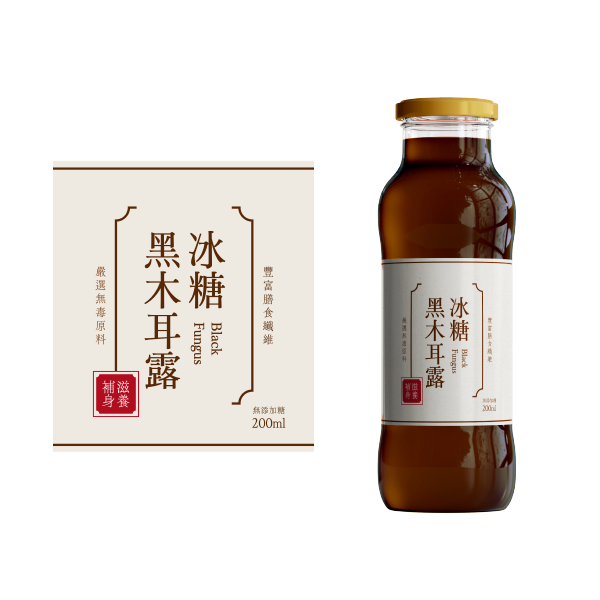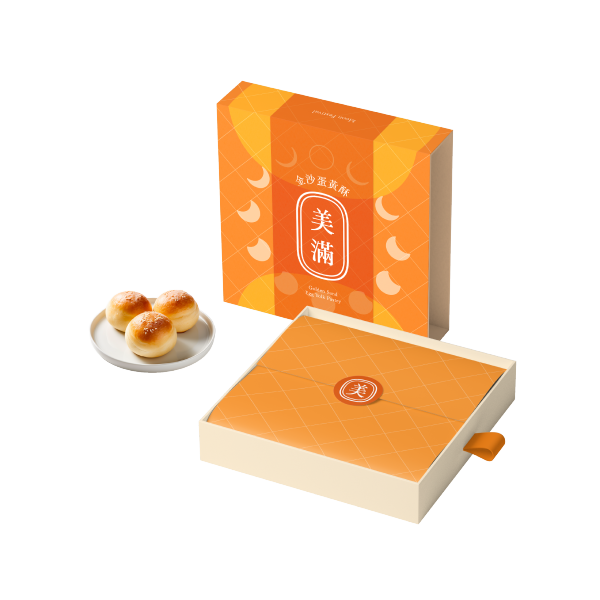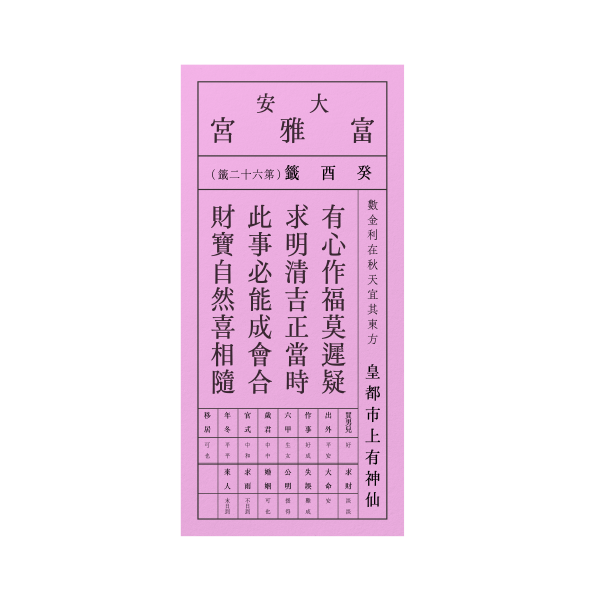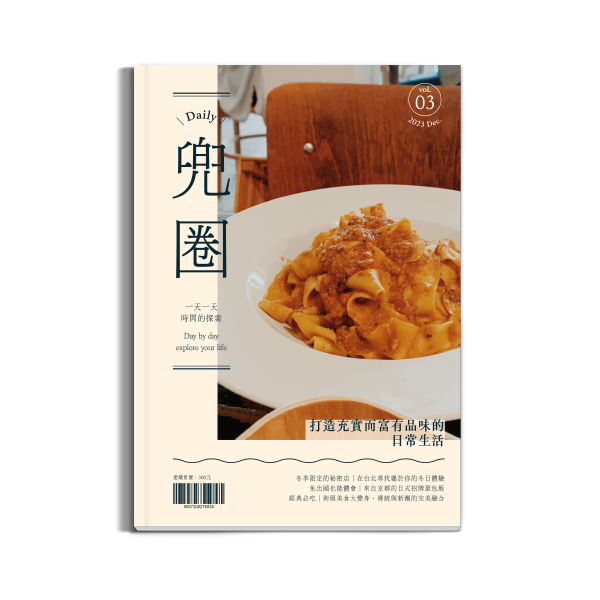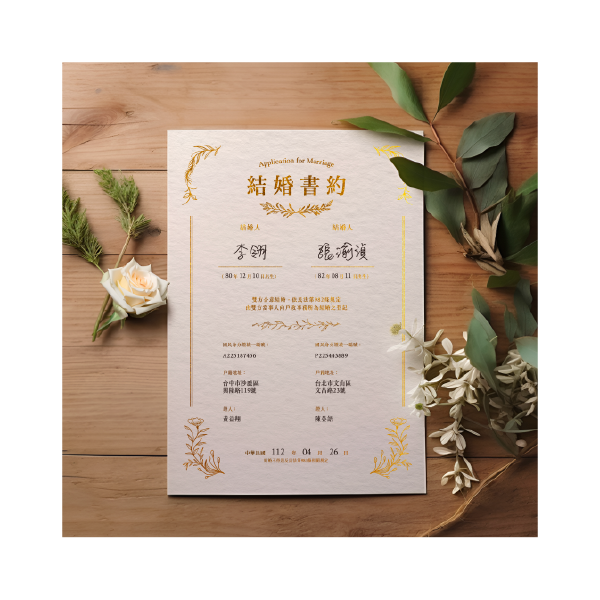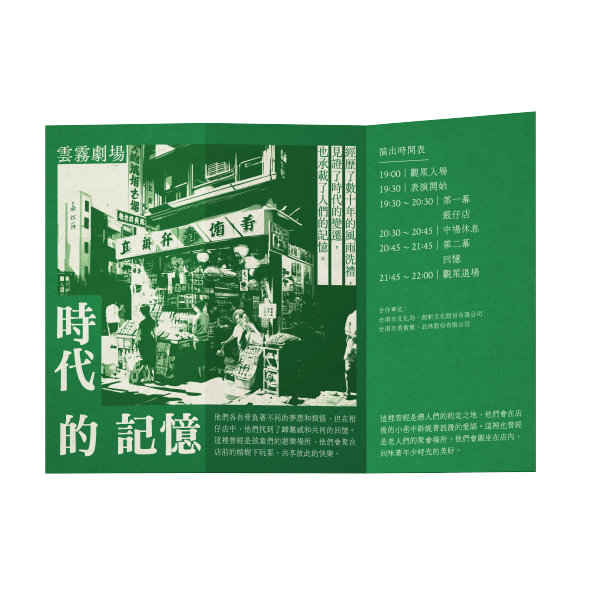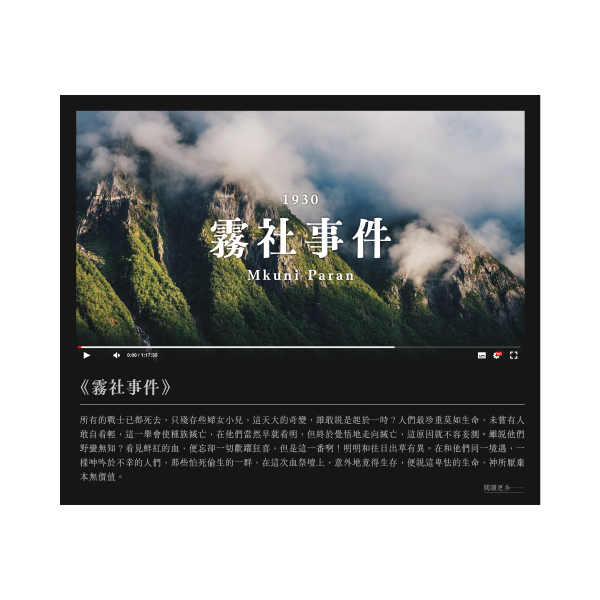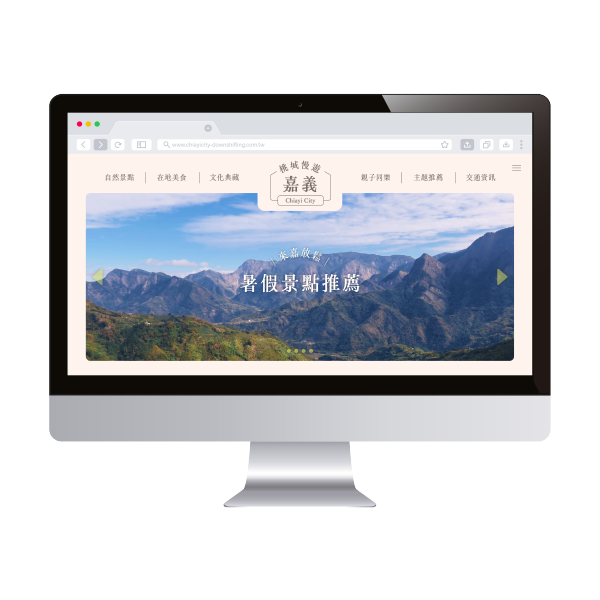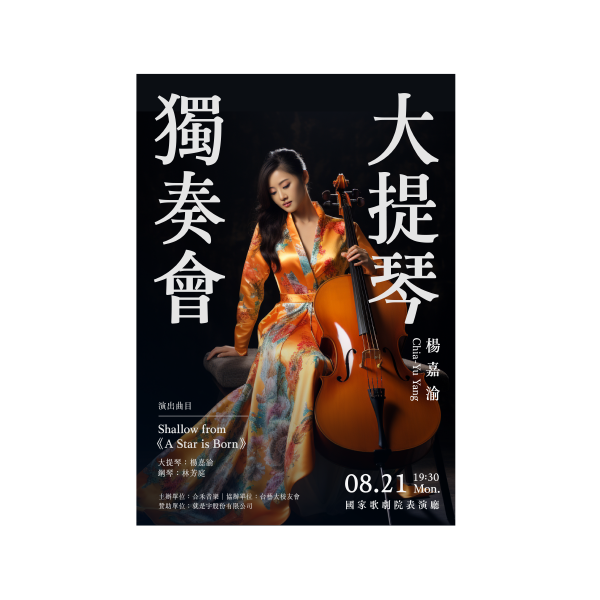
jf 蘭陽明體
書寫如詩字體,交給你結字成詩。
融合古典浪漫氛圍與現代明體筆法,
帶來感動人心的閱讀體驗。
字型設計師
林霞
宜蘭人,justfont 字體總監,30 年字體設計經驗。催生金萱、金萱那提與蘭陽等字型系列,並在凝書體、激燃體與臺灣道路體創作過程中擔任總顧問。喜歡開車。每天一號表情盯著螢幕,幻想著今天到印度,下一站到歐洲,然後再計劃到南美洲,環遊世界。